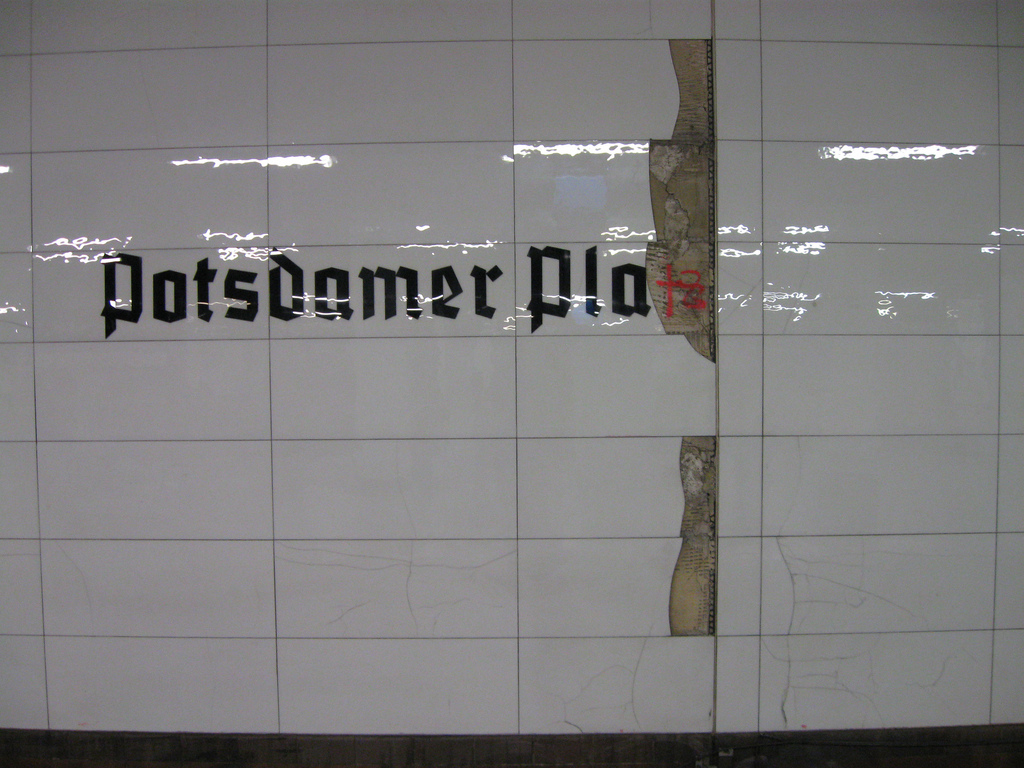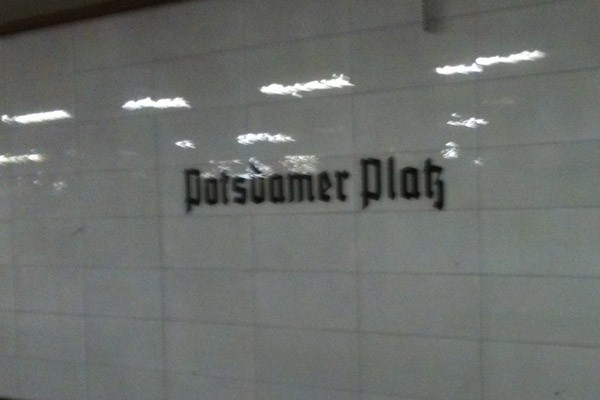
Gebrochene im Berliner S-Bahn Nordbahnhof
mich faszinieren gerade die verrufenen Schaftstiefelgrotesken ...
besonders aufgefallen ist mir bei meinem letzten Berlin-Besuch die Gotische in der Station Nordbahnhof - S-Bahn-Berlin.
Es ist nicht die Tannenberg und nicht die Potsdam. Ich hab vor kurzem irgendwo gelesen, dass die Station mit den Schriften nostalgisch restauriert wurde. Ist es möglicherweise eine Neuauflage mit kleinen Veränderungen?
Diese Schrift hat ziemlich flache Winkel in den Balken
gestern hab ich der s-bahn gmbh eine mail geschrieben. mal schauen, ob am montag eine antwort kommt.
jepp, die ist mir auch schon aufgefallen und ich find es toll das die berliner verkehrsbetriebe diese schilder auch nicht abmontieren und gegen neue austauschen. ich glaube jedoch nicht das die schrift auf einer 'bleisatzschrift' basiert. da waren sicherlich schildermaler am werk. achso: mein foto stammt, sofern ich mich erinnern kann von einer stadion auf dem alex. nicht aus dem hauptgebäude sondern von einem nebeneingang. ich kann mich aber auch täuschen, ist schon ein paar jahre her als ich das foto geschossen habe.
du, ich hab mal was gelesen, dass die schilder teilweise erst wieder im nachhinein montiert wurden - so quasi aus nostalgie. bin mir da aber nicht sicher...
die s-bahn gmbh hat mir auch schon geantwortet:
"Beim Nordbahnhof wurde die ehemalige Originalschriftart nachempfunden, da
der frühere Name ursprünglich "Stettiner Bahnhof" lautete. Aber auch auf
mehreren anderen Stationen werden Sie diese Schriftart finden: Diese
Bahnhöfe wurden in den 30er Jahren des vorherigen Jahrhunderts oder sogar
noch früher eröffnet. Aus Gründen des Denkmalschutzes blieb daher diese
Schriftart für die Nachwelt erhalten. So beispielsweise auch in
"Oranienburger Straße", "Potsdamer Platz", "Anhalter Bahnhof" und
"Wannsee".
Unseren Recherchen zufolge handelt es sich um die "Tannenberg"-Schrift, die
zur damaligen Zeit sehr populär war. Tatsächlich wurde sie aber durch den
"Normalschrifterlass" vom 3. Januar 1941 aufgegeben. Für weitere
Informationen empfehlen wir eine Recherche im Internet zu diesem Thema bzw.
mit diesen Stichworten."
... "Potsdamer Platz"...
(wenn auch etwas unscharf)
Die Fliesen haben "Platz" wohl zu wörtlich genommen … ;-)
die Element
von Max Bitroff
aber in einigen Details anders. aber das ist sie wohl
is ja bei schildermalerInnen wahrscheinlich nicht so eng, wie heutzutage mit den fonts...
news. die s-bahn gmbh hat mich jetzt noch an das berliner denkmalschutzamt weitergeleitet. mal schaun, ob die antworten.